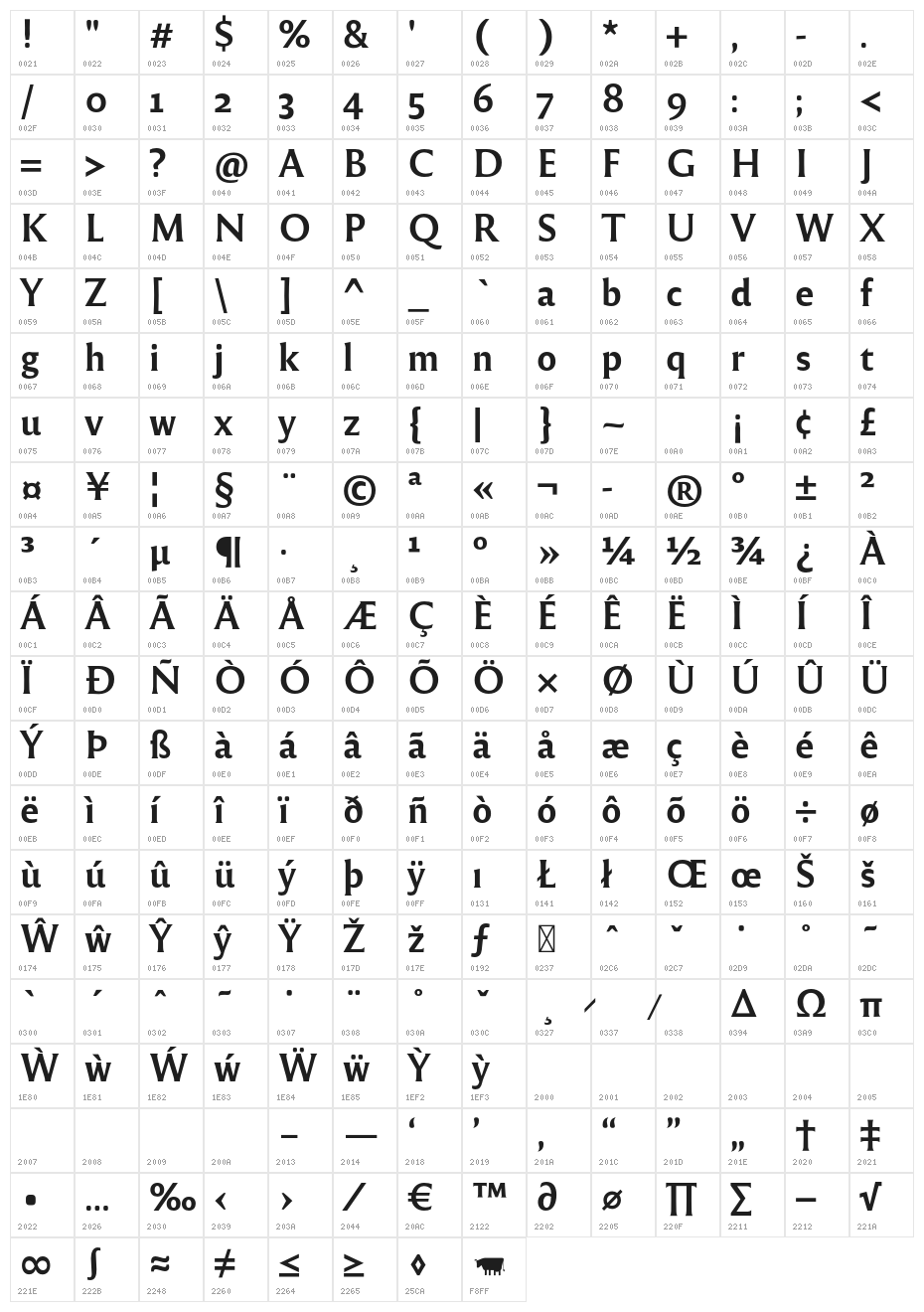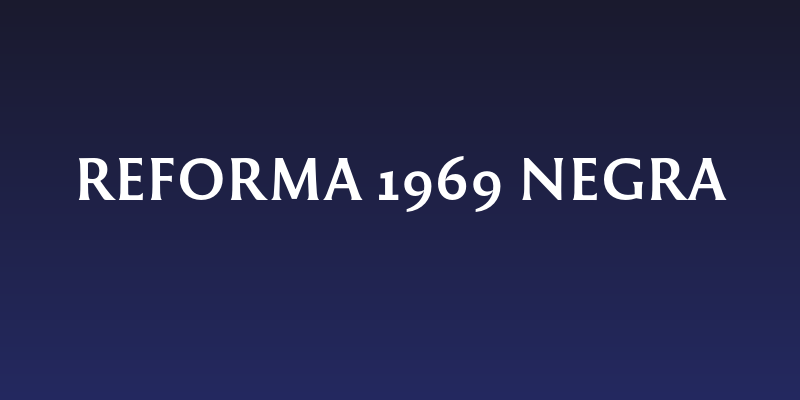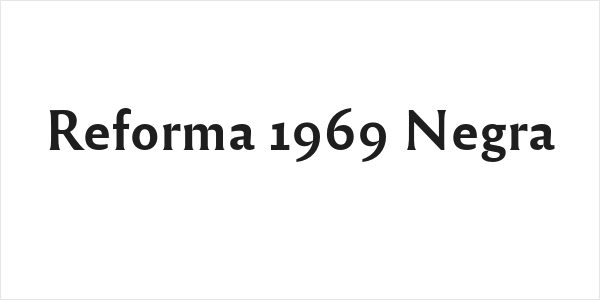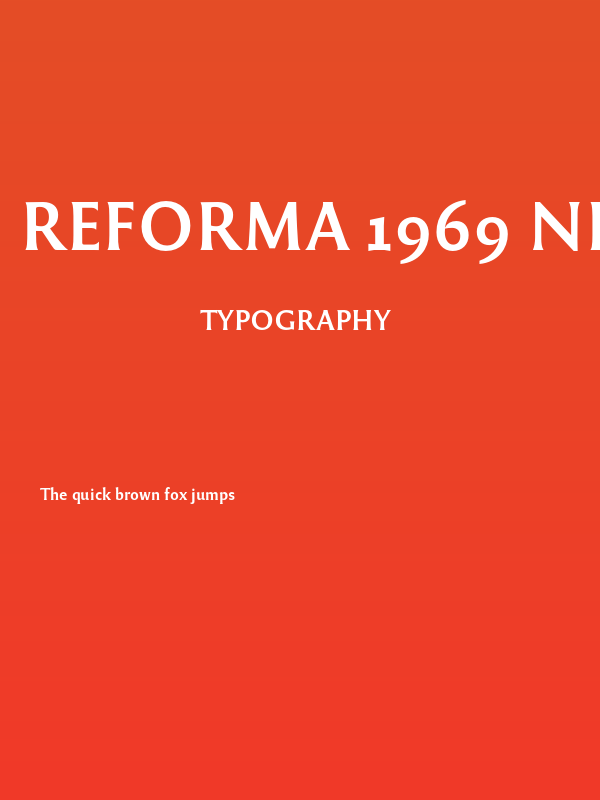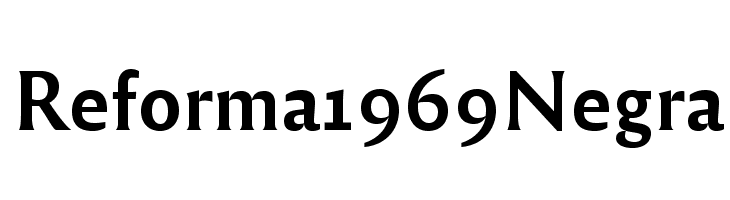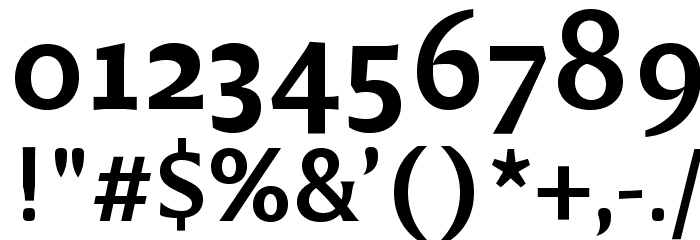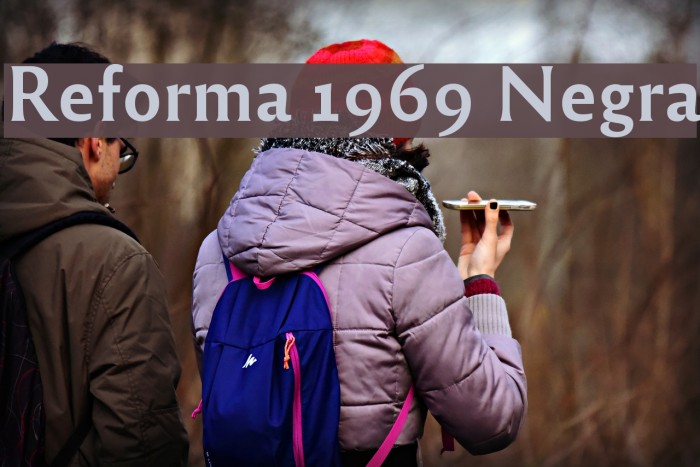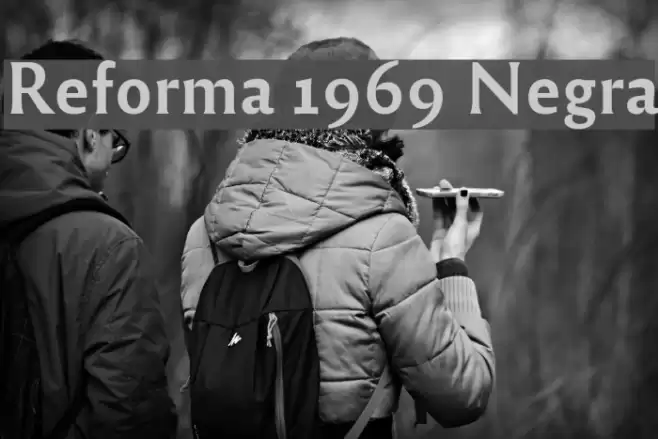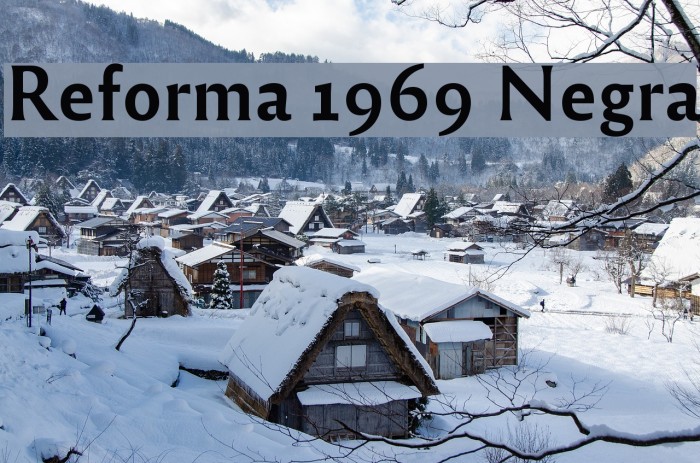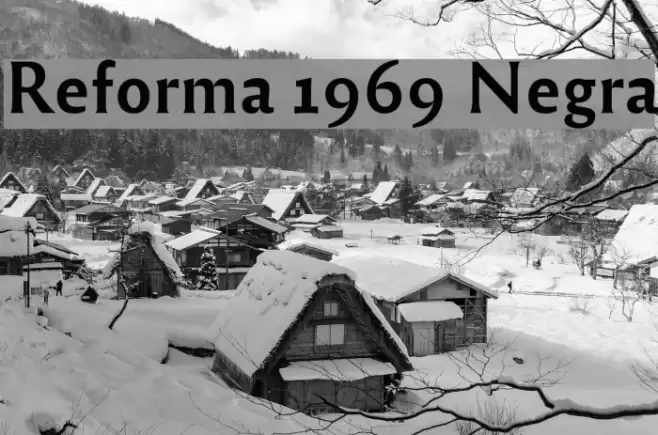
Reforma 1969 Negra Font
| Anwendungsfall | Headlines, Logos, Editorial design |
| Vorgeschlagene Projekte | Ideal for branding, editorial design, headlines, and advertising materials where a strong, modern serif is desired. |